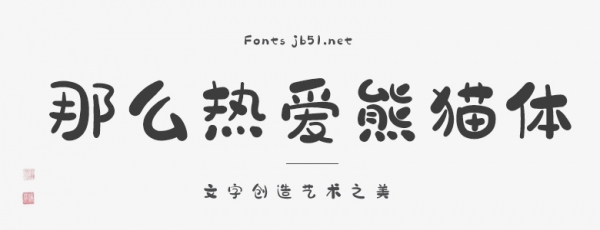
那么熱愛熊貓體是一款以“熊貓”外形為創(chuàng)意點的藝術(shù)字體,字體圓潤飽滿,每個字都似一只憨態(tài)可掬的大熊貓。整套字體可愛圓潤,略帶古風(fēng)氣質(zhì),每個字雖然胖,但卻又靈巧精致,讓人看后頓覺可愛,神情放松,心態(tài)愉悅。適用場景:標(biāo)志、包裝、海報、廣告、招牌、漫畫、游戲、兒童讀物、綜藝節(jié)目、電影劇集等,歡迎喜歡此字體的朋友前來下載使用。